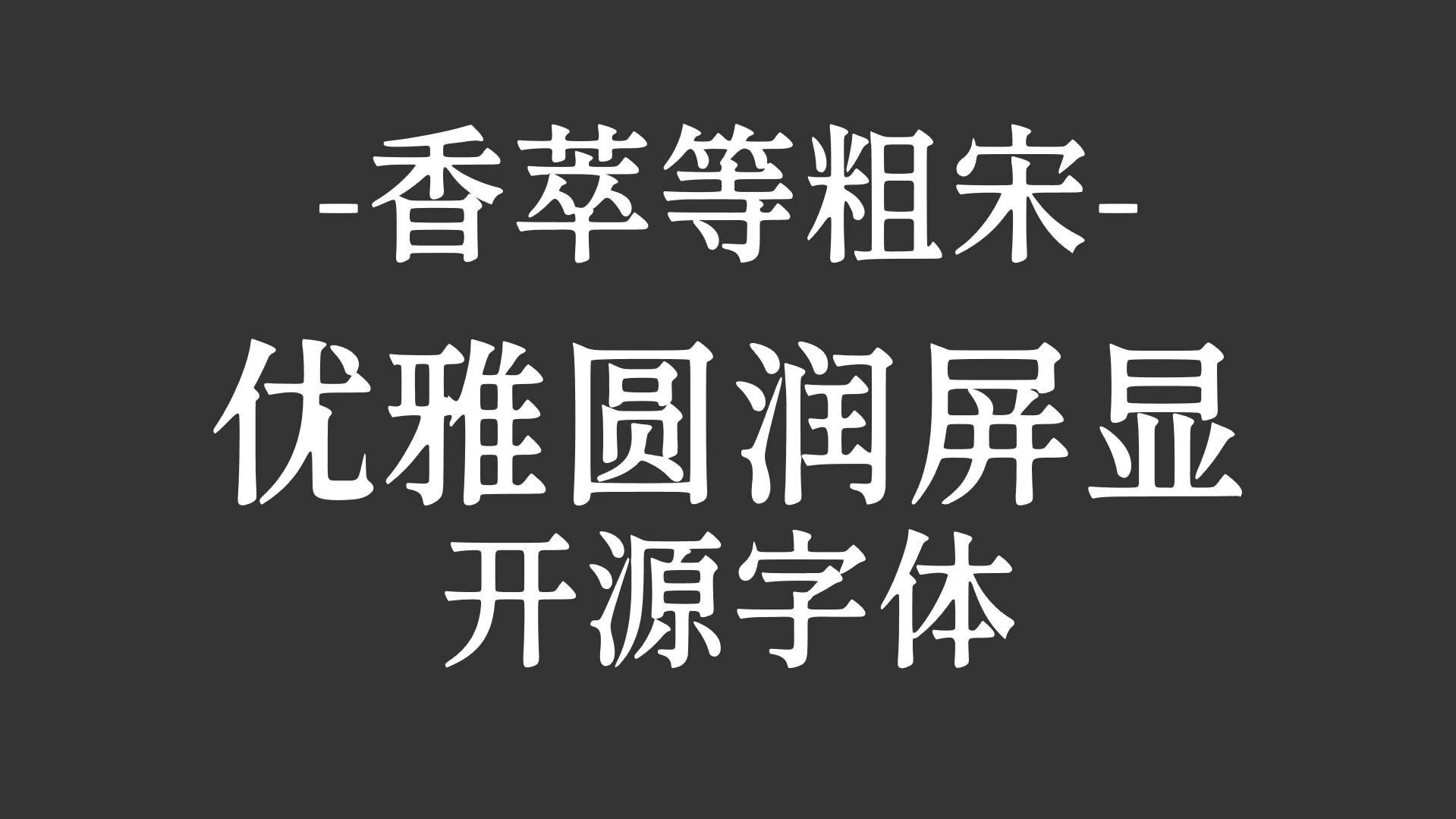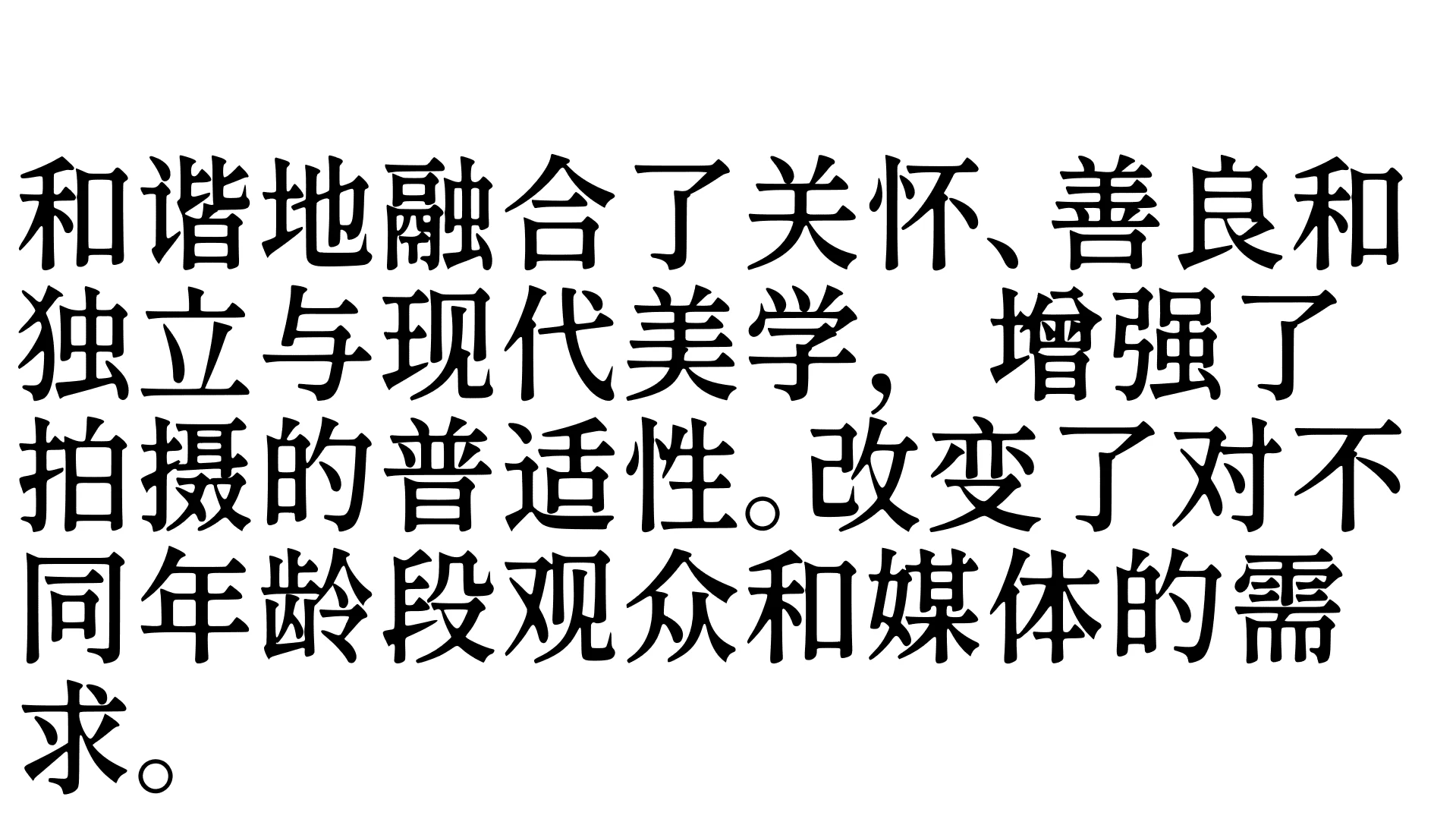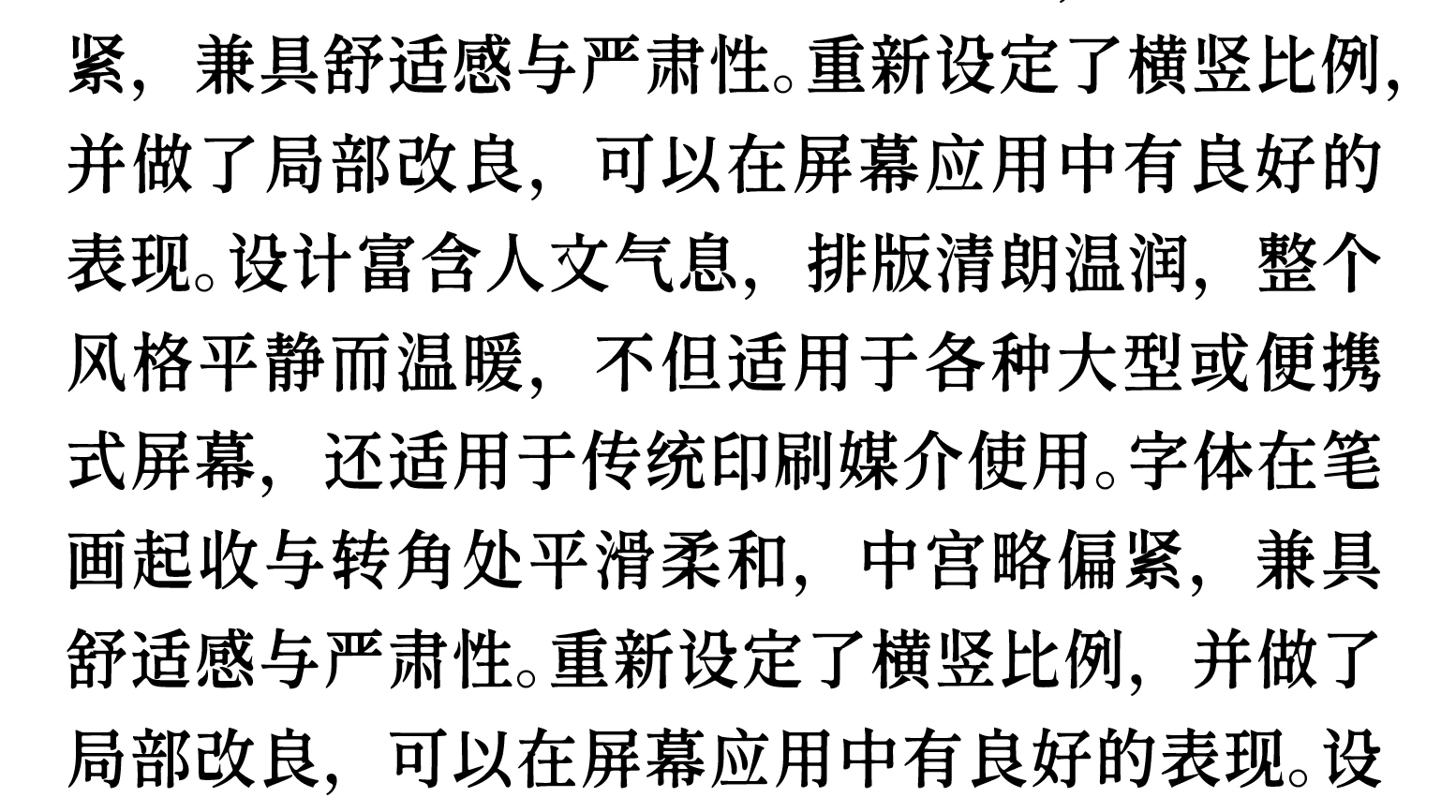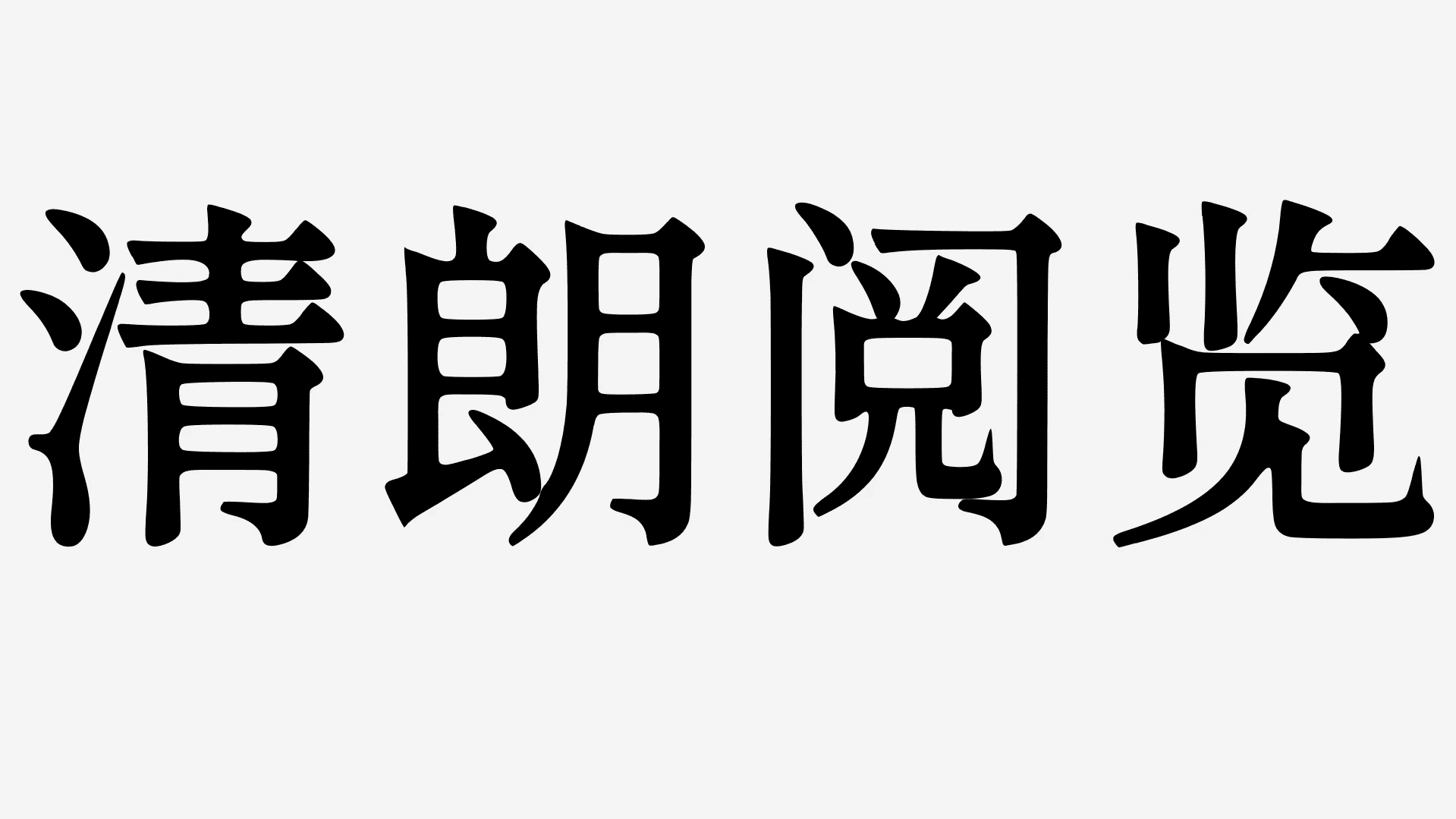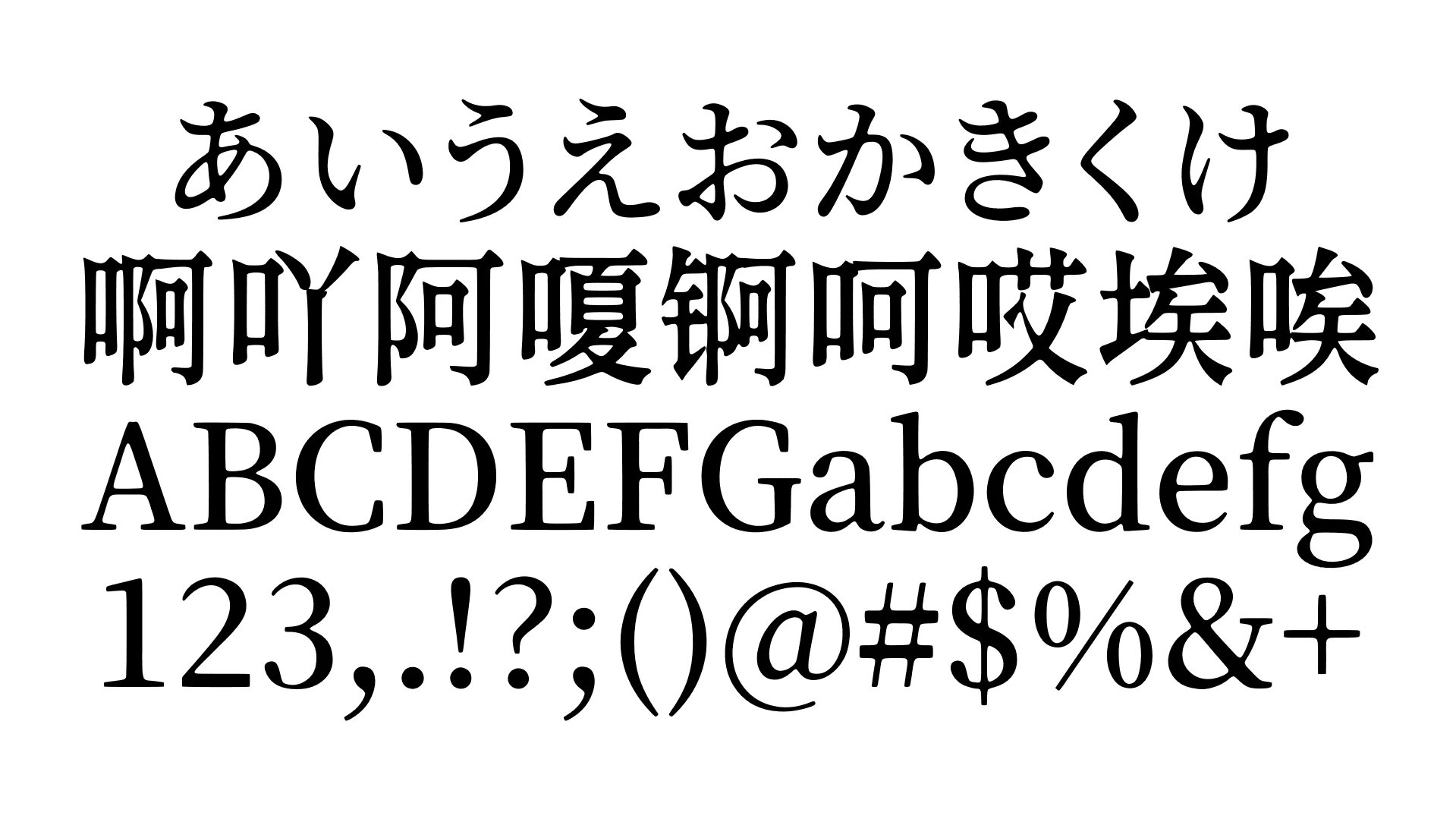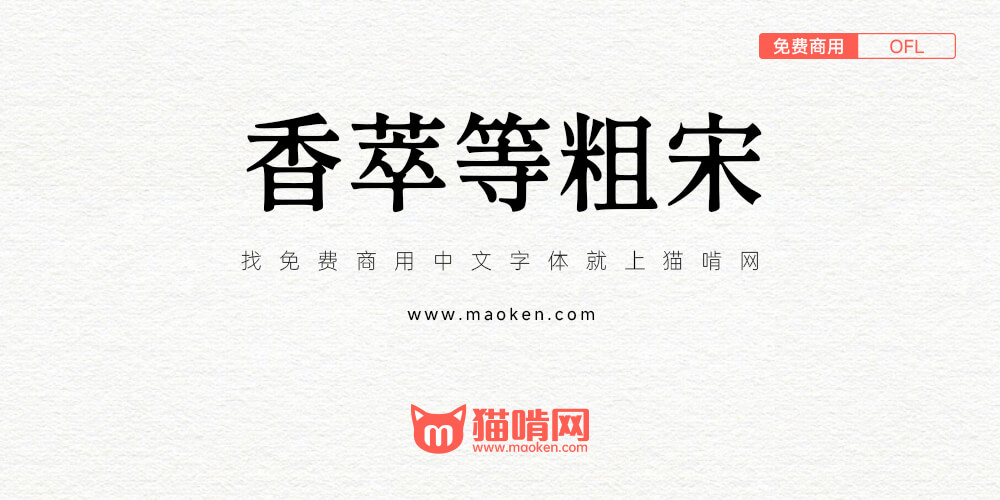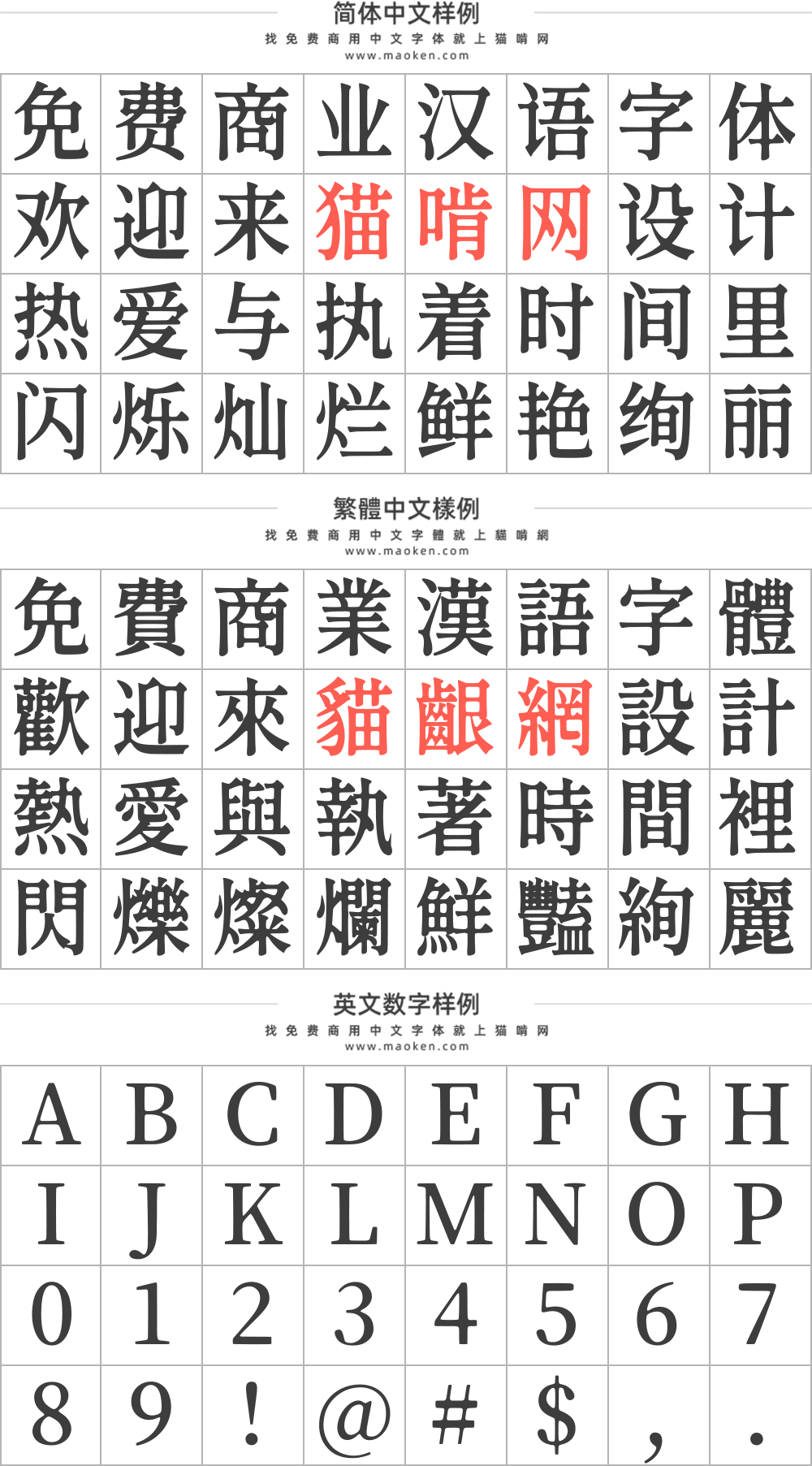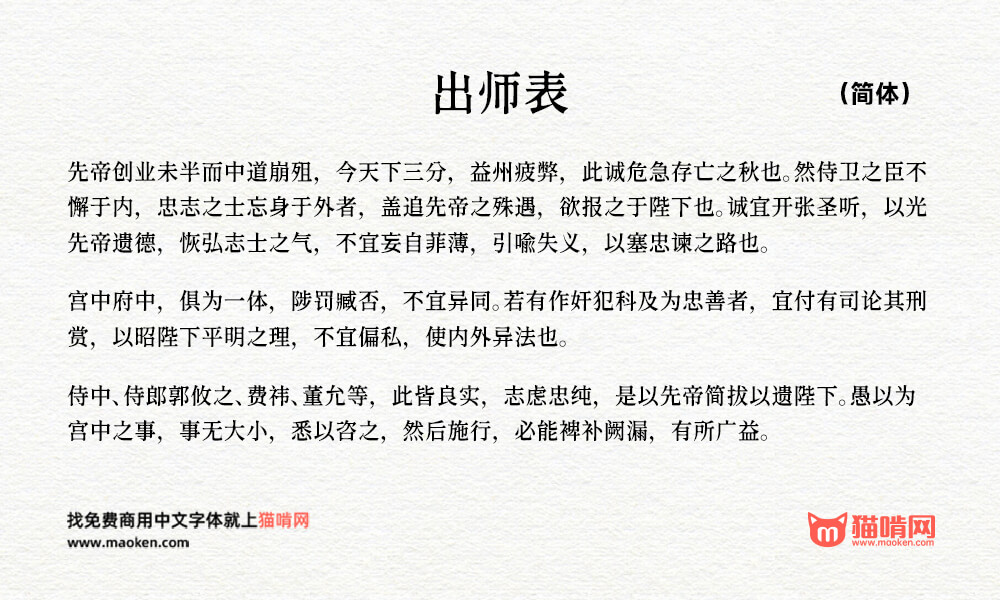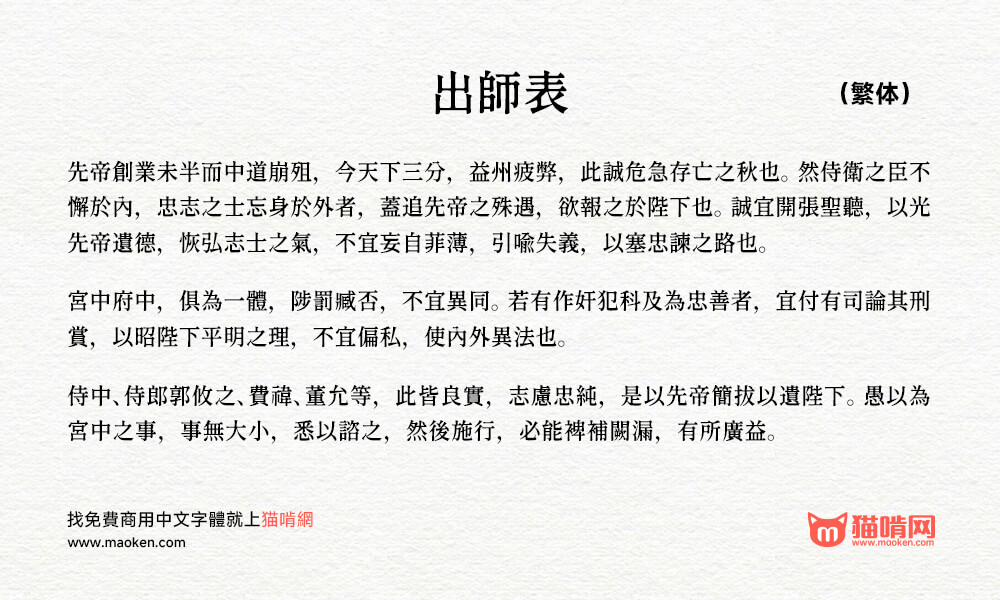
| 字体作者:Barnaos (中国大陆) | 字体字重:1个 |
字体在笔画起收与转角处平滑柔和,中宫略偏紧,兼具舒适感与严肃性。重新设定了横竖比例,并做了局部改良,可以在屏幕应用中有良好的表现。
设计富含人文气息,排版清朗温润,整个风格平静而温暖,不但适用于各种大型或便携式屏幕,还适用于传统印刷媒介使用。
字体涵盖泛中日韩超20000字符,可放心使用。对于含有旧字形的汉字,除“浅残践劲茎径禅蝉惮箪莽蟒类器”等字使用中国大陆规范字形,其余使用旧字形。
不理解为何句号是窄的,而逗号是全角的,一般中文字体若特意作不等宽标点,不是反过来吗。
虽说旧字形,但预览图中一眼看到“中宫略偏紧”里最黑的“紧”字等糸字底的不旧,还因为糸笔画过粗糊起来了。似可如此修改:
对于含有旧字形的汉字,除“浅残践劲茎径禅蝉惮箪莽蟒类器”等字使用中国大陆规范字形,其余使用旧字形。
——这句话的意思大概是简体字不用旧字形
主要这些偏旁不统一导致不太好使(预览图中还特地列出螺和骡、娜和哪不一致),甚至因为字形加了模糊滤镜,我也不好修改。